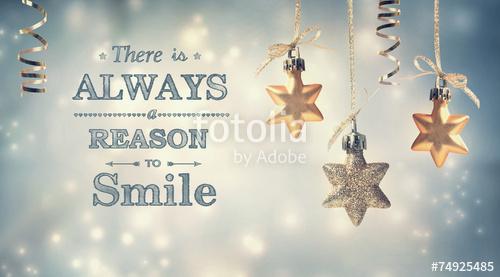
Wer kennt diese Schriftart
Hallo, ich bin etwas verzweifelt. Ich habe diese Schriftart gesucht aber nicht gefunden. Ich meine den Text Always, Reason und Smile. Vielleicht kann mir ja jemand helfen. Danke schon mal.
Meinst du mit diesen strukturierten¹ Flächen? Die kommen nicht von den Schriften, sondern wurden vom Gestalter dieser Bilderserie per Software erzeugt. Es gibt allerdings Schriften, die solche Strukturierung schon eingebaut haben. Sie z.B.
oder auch
1. Sagt man das so am besten? Auf Englisch würde ich textured sagen. :-?
»Reason« wird die Bookman sein. Für »Always« und »Smile« gibt es dutzende Möglichkeiten; die New Century Schoolbook oder andere Century-Varianten dürften nahe drankommen. Ganz unterirdische Schriftmischung übrigens.